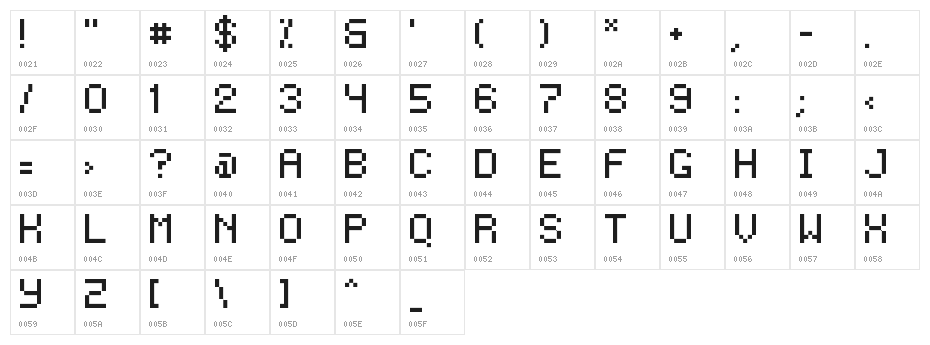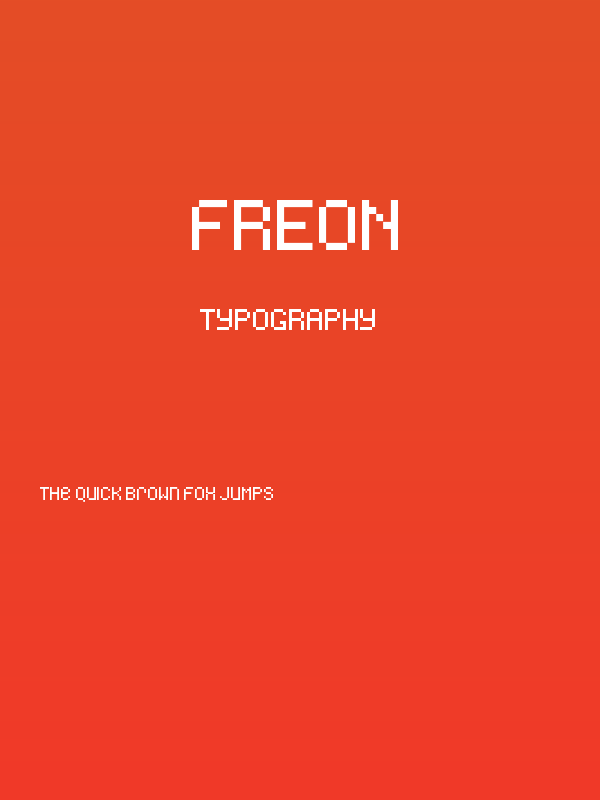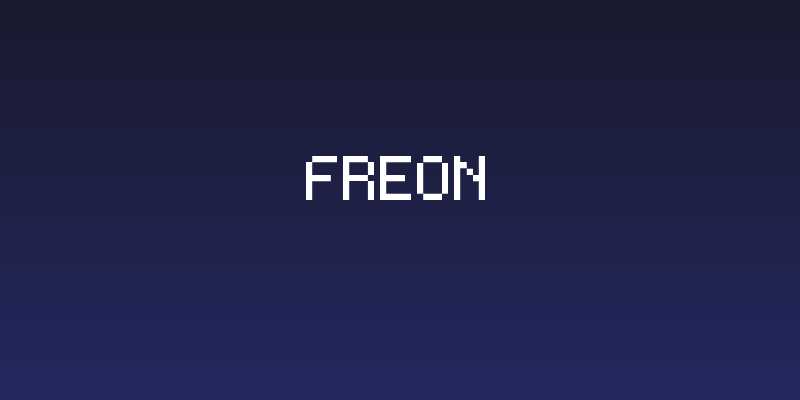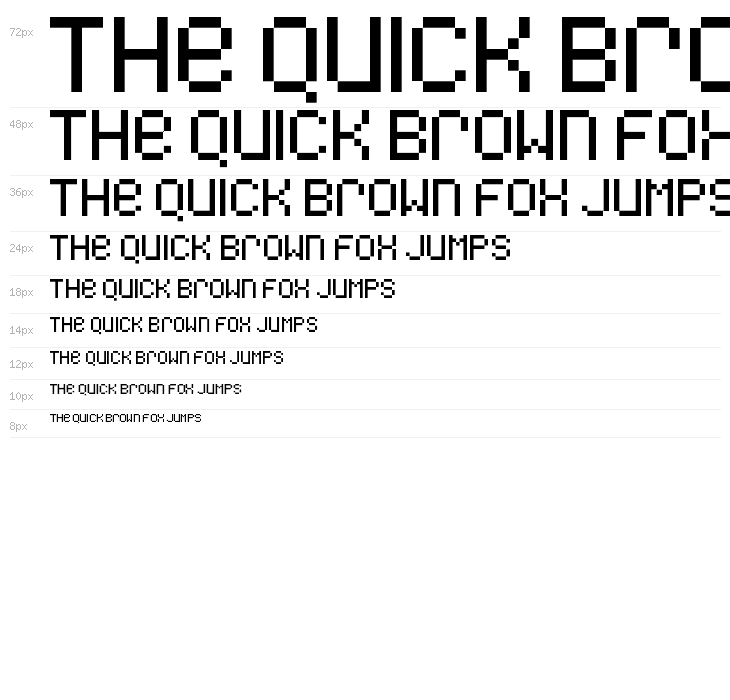
Freon Font
✎ Pixel
| Caso d'uso | Logos, Headlines, Digital Art |
| Progetti proposti | Ideal for retro-themed designs, video game graphics, digital art projects, and any creative work that seeks to evoke nostalgia for early computing. |